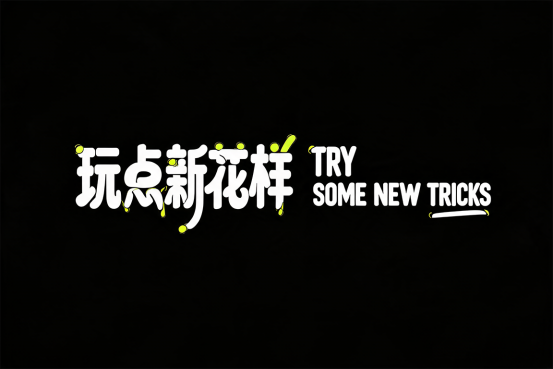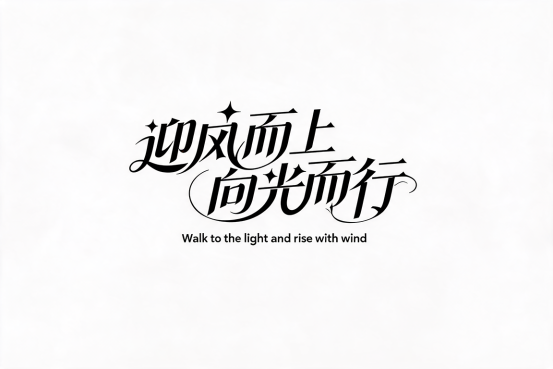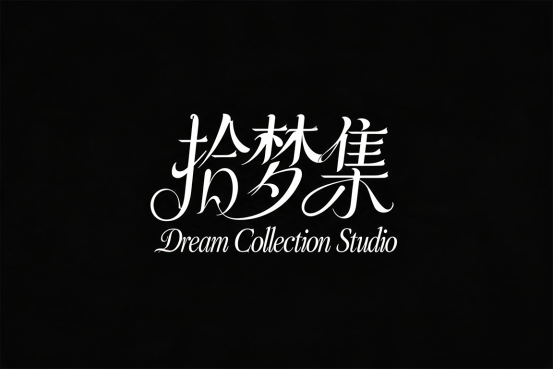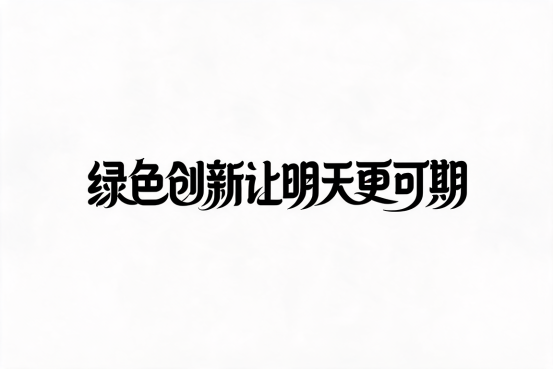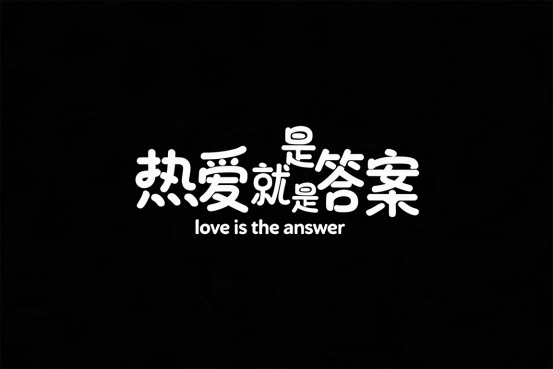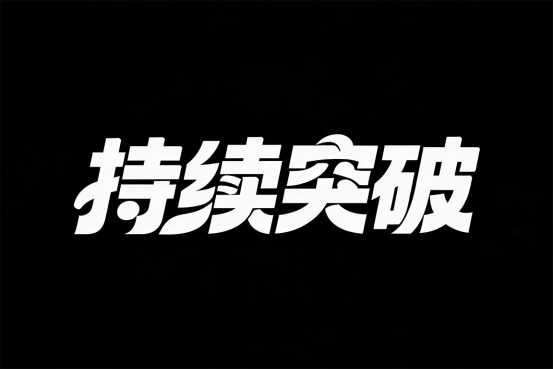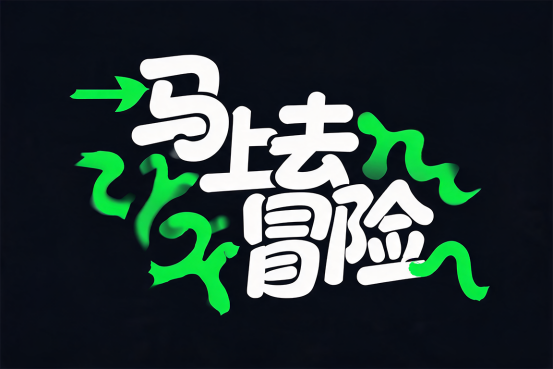
9组封神级AI艺术字体提示词!海报/Logo/标题一键生成
做海报、主视觉、品牌Logo、小红书封面,字体永远是画面的灵魂。很多时候画面质感差、高级感不足,不是排版问题,而是字体普通、风格不统一。本文整理9套可直接一键复用的AI艺术字体提示词,涵盖潮流派对、励志国风、极简高级、青春公益、情感治愈、科幻未来、冒险潮流、诗意手写等全场景。搭配 PS StartAI插件(即梦修图) 零门槛一键生成,无需手绘、无需建模,10秒出高级标题字效,非常适合设计师、运营、自媒体、品牌美工日常出图。
0 前言:解决90%设计人的字体痛点
绝大多数新手、兼职美工都会遇到这几个难题:
1、海报画面做好了,普通免费字体太呆板、没有氛围,撑不起画面质感;
今天给大家整理 9套成品AI字体提示词模版,覆盖9大主流设计风格,直接复制、改文字、一键生成,适配海报、Logo、封面、主视觉、活动banner。
一、高效生成工具:PS StartAI即梦修图(零门槛)
操作优势
无需手绘、无需建模、无需上传参考图,纯文字提示词一键生成艺术字体,风格统一、细节高级。
实操步骤
2、选择【即梦修图】功能,无需上传图片,直接输入提示词;
3、替换自己需要的文字内容,设置图片比例;
4、点击生成,自动输出高清艺术字体标题,可直接用于海报、Logo、封面。
二、9套可直接复用的AI艺术字体提示词(全场景覆盖)
01、潮流派对体|活动/快闪/年轻化海报专用
适配场景:派对活动、快闪海报、潮流线下活动、年轻品牌造势
AI提示词:生成潮流派对风格艺术字体,内容为“玩点新花样”,搭配英文“TRY SOME NEW TRICKS”进行排版。同一行字,不分组,运营活动风格主题字体,字体大小变化明显,错落有致排版。部分笔画延长,字体笔画粗厚醒目,形态夸张变形,部分笔画带俏皮弧度或独特弯折,营造活泼、肆意、充满活力的派对氛围,黄绿色点缀。黑色背景,背景干净。白色字体,大师作品。
02、追光迎风体|励志/年会/品牌Slogan专用
适配场景:企业年会、励志海报、品牌宣言、团队主视觉、毕业海报
AI提示词:创意字体设计“迎风而上向光而行”,加入小字英文“Walk to the light and rise with wind”进行排版,字体居中画面,字体设计富有动感与活力,笔画线条流畅、舒展且具有艺术感,将字体进行抽象变形,相邻字的笔划可以连笔和共用。夸张的笔画弧度,字体造型充满动感且棱角分明,融合尖锐边缘与流畅曲线,营造出大胆、视觉冲击力强的装饰性字体效果,笔画转角圆角处理,笔画延伸,居于画面中心,简约而强大。部分笔画融入四角星形,让整体更准确地表达和贴近主题。白底黑字,纯色的背景。
03、极简梦境体|文创/展览/工作室LOGO专用
适配场景:文创品牌、艺术展览、个人工作室Logo、文艺封面、极简海报
AI提示词:线条流畅且富有艺术感,中文“拾梦集”,创意字体设计,英文“Dream Collection Studio”设计灵感,将字体进行抽象变形,创造出独特的节奏和动感,给人以强烈的视觉冲击。黑底白字,高级感,扁平化,大师作品。
04、绿动青春体|校园/环保/青年活动专用
适配场景:校园活动、环保公益、青年论坛、青春主题宣传海报
AI提示词:字体设计,白底黑字,无衬线字体设计“绿色创新让明天更可期”,相邻笔划可以连笔,字体笔画粗厚醒目,创造出独特的节奏和动感,给人以强烈的视觉冲击。整体结构规整,通过笔画的变形与点缀,呈现出时尚、新颖的视觉效果,契合青春、活力的主题。
05、热爱律动体|情感/应援/告白场景专用
适配场景:情感海报、告白求婚、粉丝应援、治愈系封面
AI提示词:黑底白字,背景为纯黑色,无其他元素干扰。创意字体设计“热爱就是答案”,搭配英文“love is the answer”进行合理排版,字体设计富有动感与活力,笔画圆润且有一定的粗细变化,字体大小变化,错位编排。呈现现代感和醒目视觉效果,文字居中排列,大师作品,高级感。
06、突破无界体|科技/创业/运动品牌专用
适配场景:科技产品宣传、创业公司海报、运动品牌主视觉、突破主题展板
AI提示词:字体设计,黑底白色,无衬线字体设计“持续突破”,相邻笔划可以连笔,字体笔画粗厚醒目,创造出独特的节奏和动感,给人以强烈的视觉冲击。整体结构规整,通过笔画的变形与点缀,呈现出时尚、新颖的视觉效果,契合青春、活力的主题。
07、冒险探索体|户外/旅行/极限运动专用
适配场景:户外品牌、旅行博主封面、极限运动、探索主题活动
AI提示词:潮流创意风格字体设计,文字内容为“马上去冒险”,字体结构错落有层次,创意变形且笔画相互穿插融合,笔画粗细对比鲜明,部分笔画圆润化并带有夸张延伸(如箭头、波浪形态),背景搭配鲜亮的荧光绿创意图形元素,整体传递出年轻时尚、充满活力与探索欲的氛围,体现“Go explore now”的创意感。
08、诗意手写体|文艺/生活/咖啡馆品牌专用
适配场景:文艺海报、生活方式品牌、咖啡馆、手账、治愈系图文
AI提示词:黑底白字,主体为现代艺术手写创意字体“把日常写成故事”;字体笔画融合柔美曲线与锐利直线,曲线飘逸延伸,直线挺拔利落;字形呈横向舒展且略带动态倾斜的布局,字间笔画相互呼应、富有视觉流动感;笔画粗细对比细腻(主笔稳重、辅笔纤细轻盈),线条边缘光滑自然;下方搭配纤细无衬线字体“Turn Daily Life Into a Story”;整体营造浪漫细腻、心动时的轻盈艺术氛围,突出字体的曲线韵律、动态布局与中英文风格融合的效果。
09、星际科幻体|科技/未来/太空主题专用
适配场景:科技公司、太空展览、未来感品牌、科幻海报、赛博视觉
AI提示词:白色背景,黑色字体,干净的背景,创意字体设计“星际漫游研究所”,加入小字英文“Galaxy Motion Creative Station”进行排版,字体居中画面,字体设计富有动感与活力,笔画线条流畅、舒展且具有艺术感,将字体进行抽象变形,相邻字的笔划可以连笔和共用。夸张的笔画弧度,字体造型充满动感且棱角分明,融合尖锐边缘与流畅曲线,营造出大胆、视觉冲击力强的装饰性字体效果,笔画转角圆角处理,笔画延伸,居于画面中心,简约而强大。部分笔画融入星球和四角形符号图形,让整体更准确的表达和贴近主题。
三、AI字体生成通用技巧(提升出图质量)
1、替换文字即可复用:所有提示词均可直接修改中文内容,风格、排版逻辑不变;
2、比例统一设置:海报标题选用16:9、封面选用1:1、竖版海报选用9:16;
3、尽量固定风格关键词:大师作品、干净背景、笔画延伸、错落排版等关键词不要随意删除;
4、多次微调:第一次生成不满意,可重新点击生成,AI会随机微调细节,大概率出精品。
四、全文总结
1、普通免费字体质感有限,AI艺术字体是当下最高效的海报提质方案;
2、9套风格覆盖:潮流派对、励志国风、极简文创、青春公益、情感治愈、科技突破、户外冒险、文艺手写、星际科幻,适配99%日常设计场景;
3、借助 PS StartAI即梦修图,无需手绘、无需专业功底,复制提示词一键生成,大幅提升设计效率与画面高级感;
4、所有模版可无限复用、改字即用,非常适合设计师、自媒体运营、美工、活动策划长期备用。